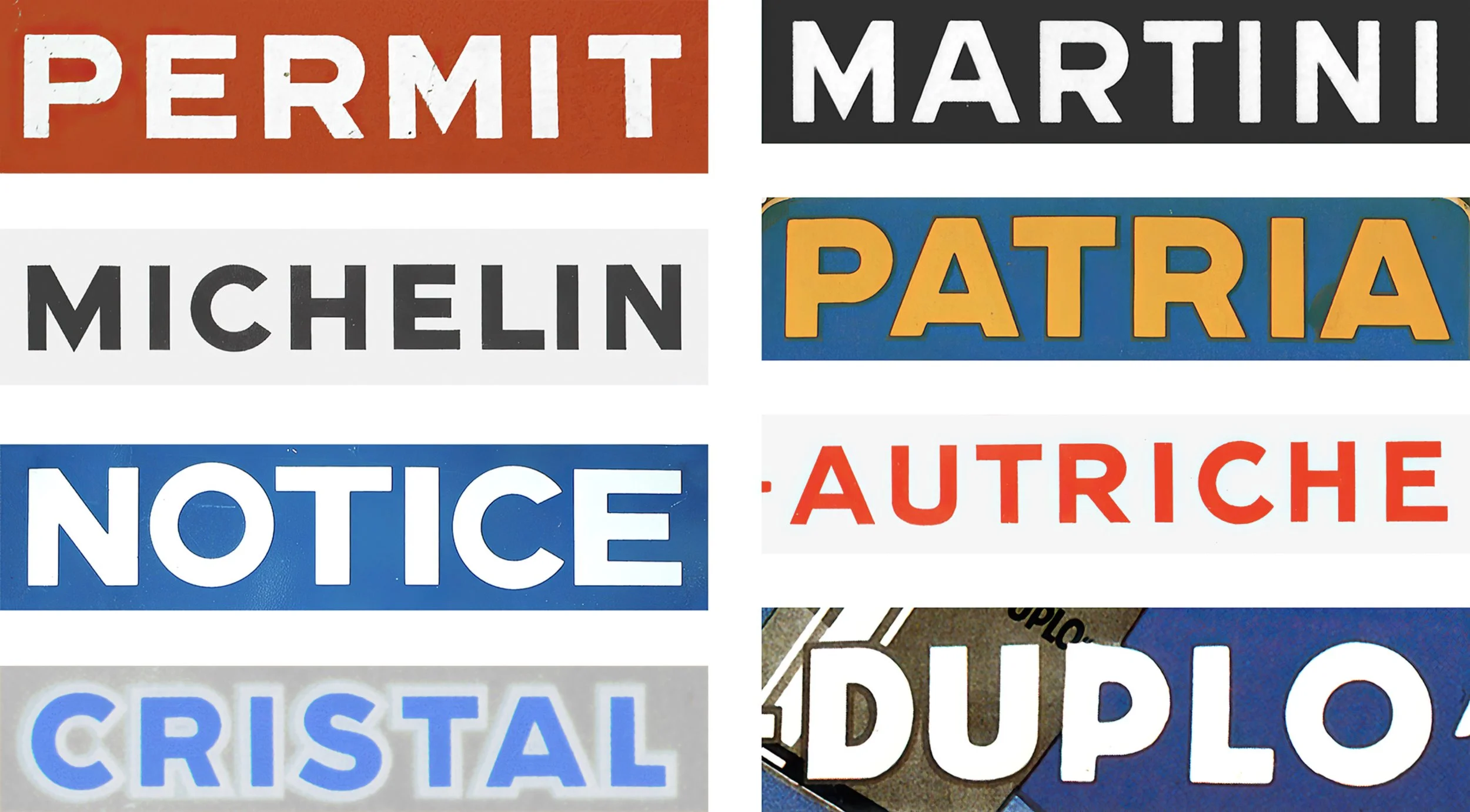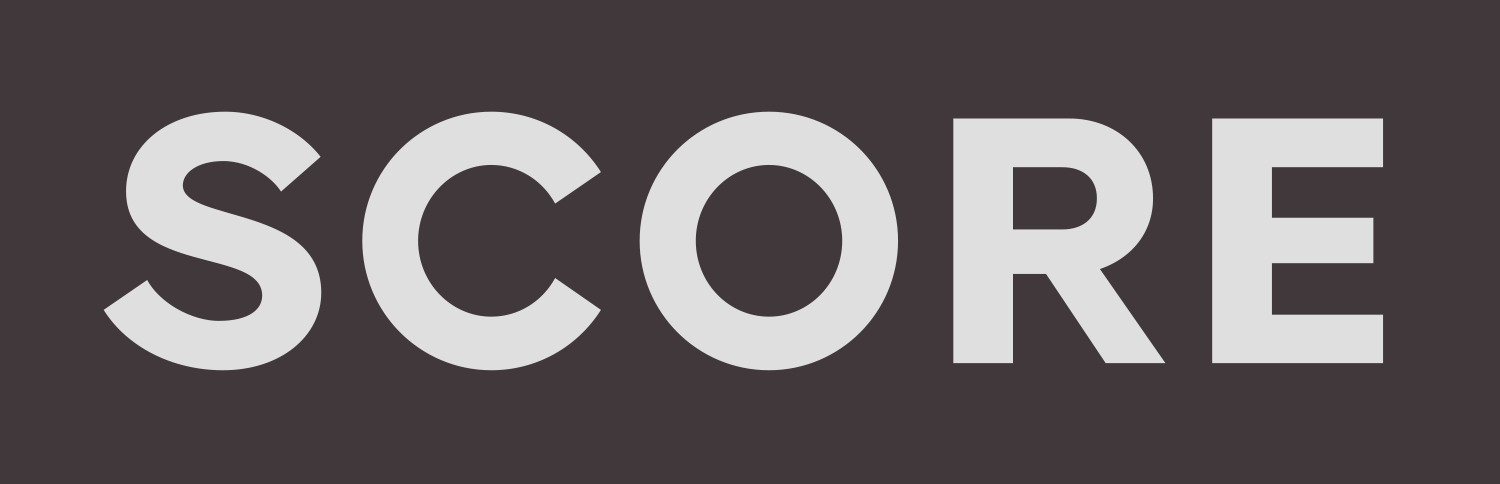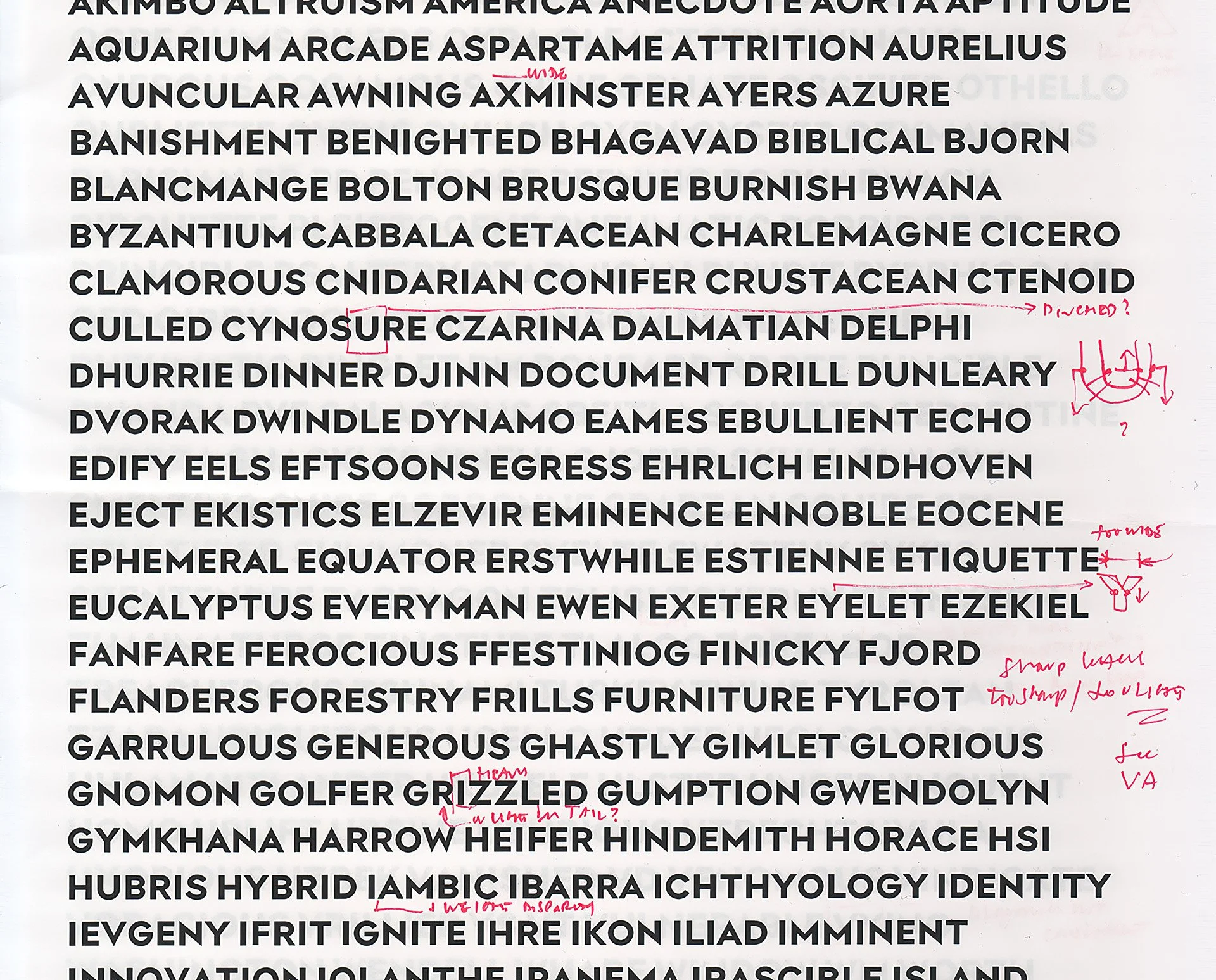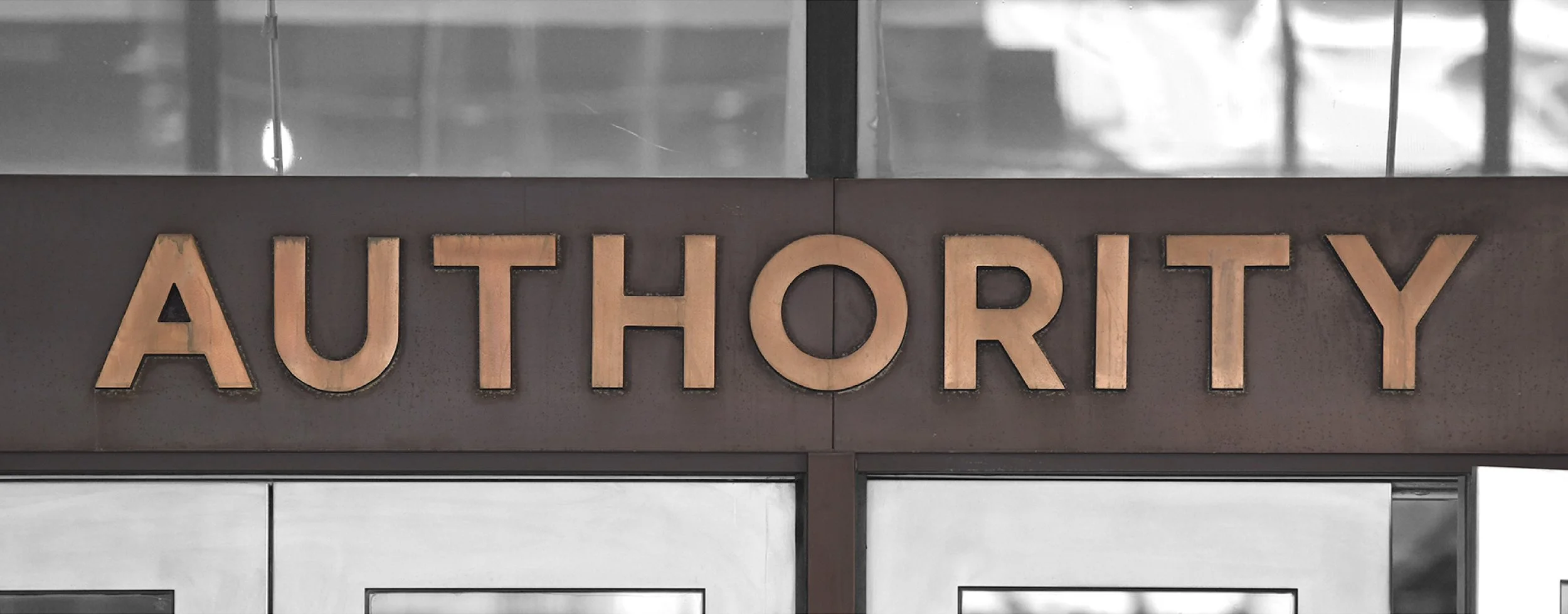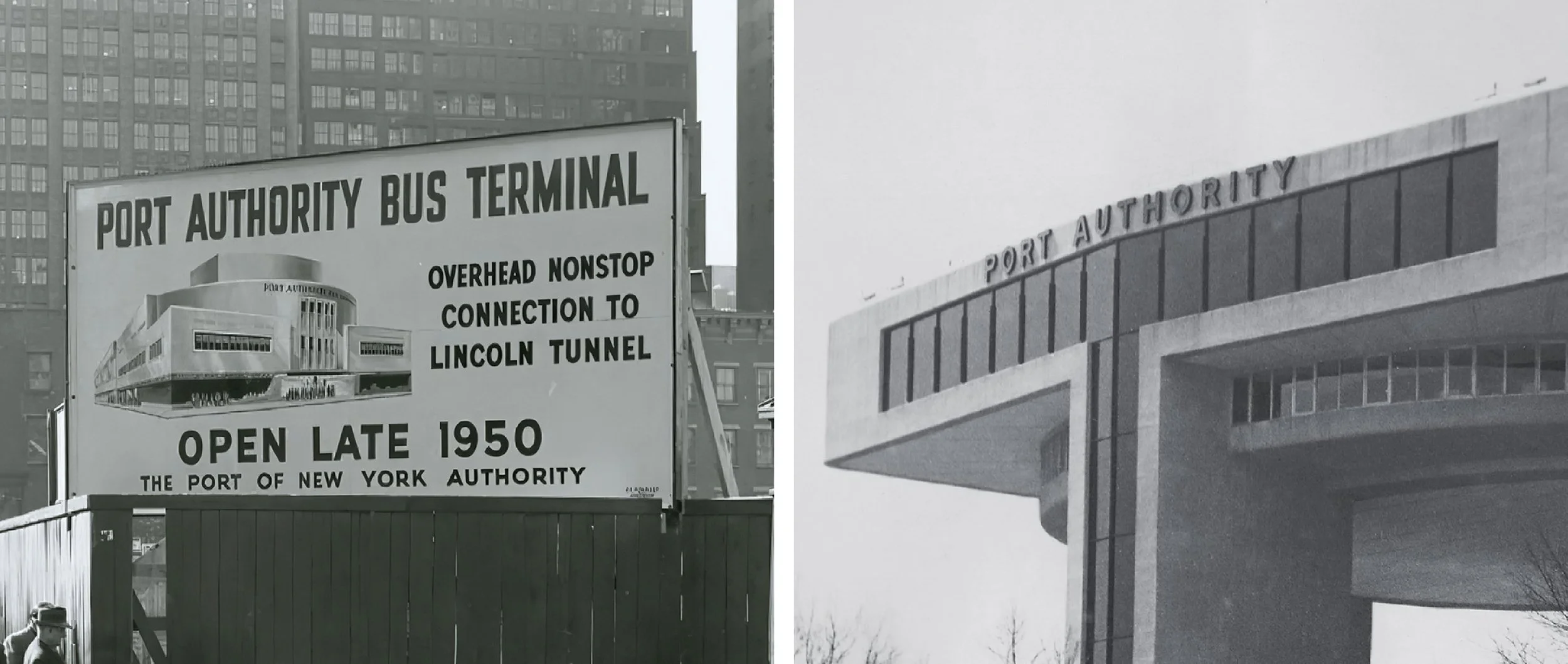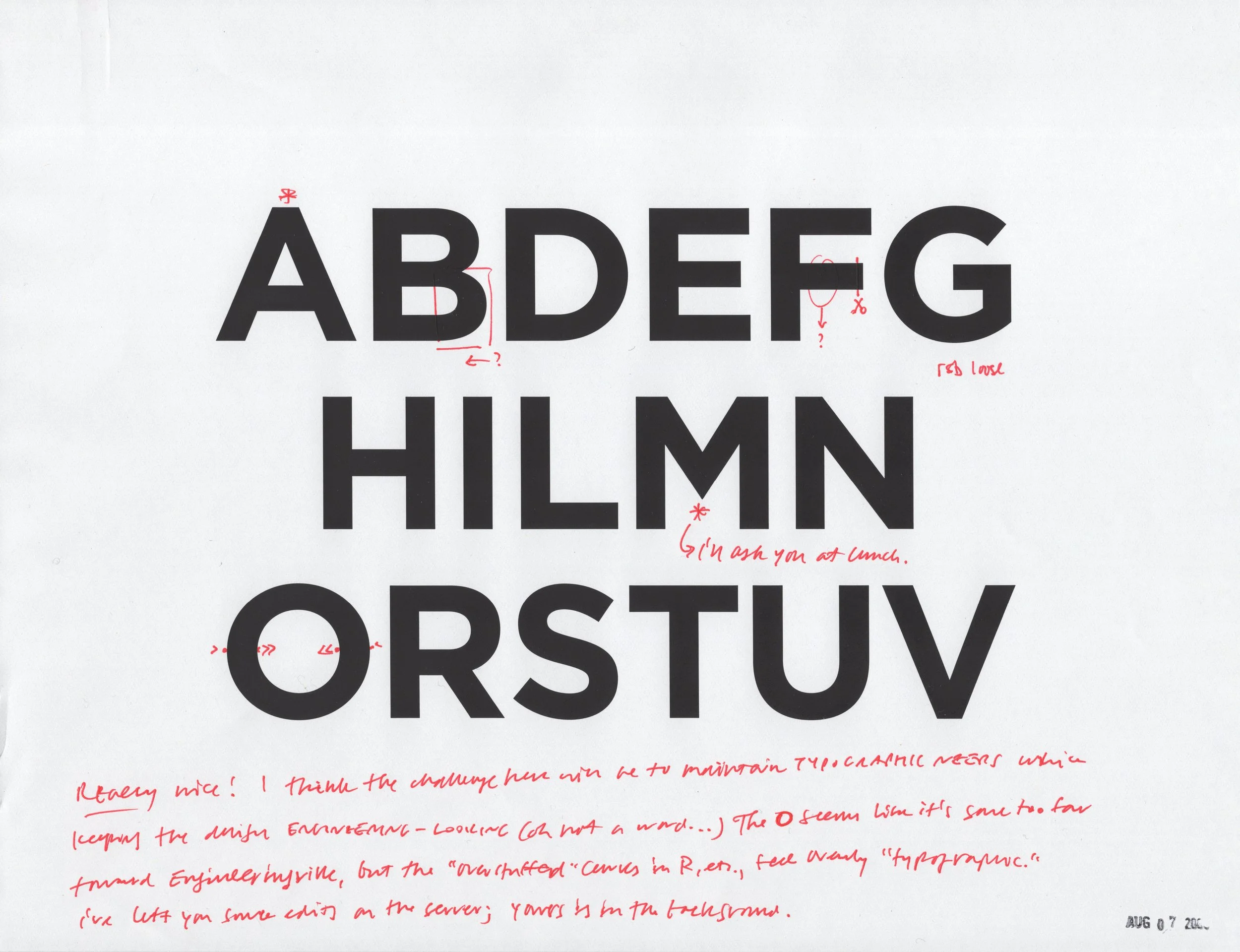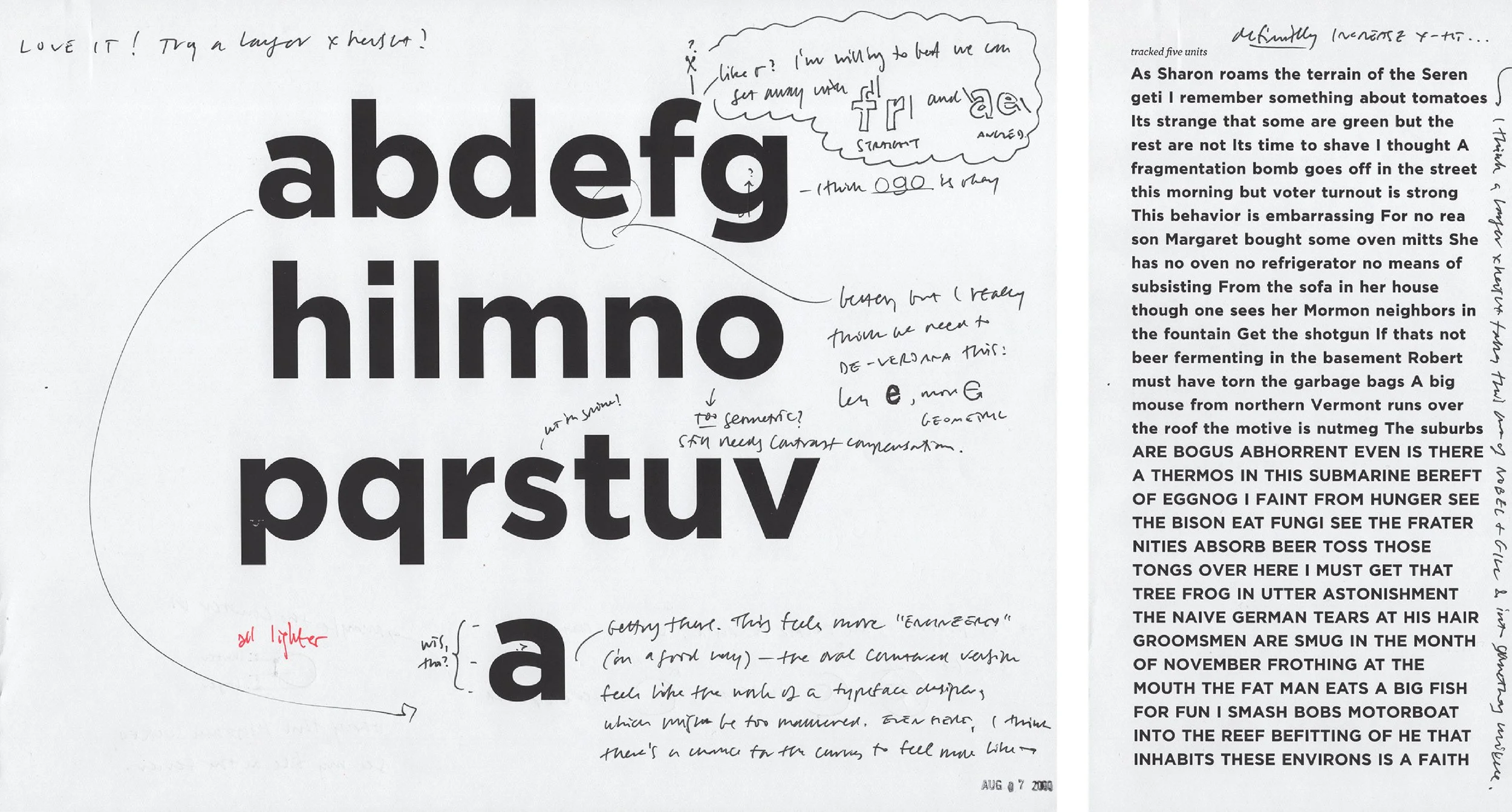
从纽约街头到总统竞选:一文读懂传奇字体 Gotham 的前世今生
如果要选出一款能代表现代城市精神的字体,Gotham 一定榜上有名。它曾出现在奥巴马 2008 年的竞选宣传中,也频繁活跃在海报、广告和品牌形象里,成为 21 世纪最具影响力的无衬线字体之一。
但它的故事,并不是从电脑屏幕开始,而是源自纽约街头那些无名却持久的字母。为什么这样「看似平凡」的字形,能够成长为全球舞台上的视觉语言?
本文改编自 Hoefler&Co. 创始人、Gotham 的设计者 Jonathan Hoefler 的自述文章,带你追溯这款字体的起源与崛起。
1 源于街头的字母灵感
这些街头字母虽然无名,但似乎一直存在,它们被画在玻璃上、铸在金属里、刻在石头上;既出现在战时通告中,也点缀过香水瓶和工业标志。但更多时候,它们出现在日常生活中:酒铺、理发店、花店的招牌,甚至电梯轿厢和商店橱窗。
设计文献几乎没有提及这些字母,这让人颇感意外。
设计潮流不断更替,但这些基本形态却始终显得现代、得体、不过时。
许多设计师的学习路径也是「倒着来」的:他们从身边现成的材料入手,再追溯字体的历史。最初,早期的 Mac 上的一百多种字体已经令人觉得丰富。但直到 1988 年,Jonathan Hoefler 进入 PushPin Group 下面的一家小型工作室,才真正接触到浩瀚的字体世界。
PushPin 的图书馆里摆满了字体样张书籍,宛如一部「化石记录」,展示着大量已随铅字与照排工艺消失的字体。夜晚,Hoefler 常在这些书里寻找理想的无衬线字体。最终他发现,这些形态并非源自传统字体,而是起于手工绘制的字母。
2 字体 VS 字母绘制
字体(Type)是预制、可重复组合的字形系统,而字母绘制(Lettering)则是一次性的、为特定场合量身定制的字形组合
。一个世纪前,字体排版只出现在书籍正文中,书籍封面、书脊或插图上的文字都是手绘字母,而非直接组合现成字体。
由于手写字母独立于字体存在,它发展出了自己独特的风格和传统:石印海报、雕刻钞票、镀金橱窗招牌、刻在墓碑上的字母,都是量身定制而非现成排版,每一种都展现了媒介特性和创作者习惯。
尽管字体与手写字母几个世纪以来互相影响(毕竟古腾堡的活字就是以手写字母为模型),但
似乎没有任何字体设计师尝试去捕捉 Hoefler 欣赏的这种手绘无衬线风格。
或许正是这个挑战,让他成为了一名字体设计师:这是一次不可抗拒的机会,可以探索未知领域,填补他感受到的空白。
3 从未竟之作到设计典范:Gotham 的诞生历程
3.1 新政雄鹰:Eagle Bold 的推出
从字体分类来看,Jonathan Hoefler 钟爱的字母,
融合了几何体的纯粹与怪诞体的温度,却避开了两者的缺陷
。它们像 Futura 一样清晰简洁,却没有几何体的刻板;它们兼具 Akzidenz-Grotesk 那种厚重亲切的特质,却比印刷字体更自然随性。
与 Helvetica 这类工业化的产物不同,这些街头字母看起来更真实可信:
不像是被「设计」出来的,而像是被「自然造就」的。
在字体与手写字母交汇的历史中,有一个值得注意的时刻,出现在罗斯福新政时期。为推动美国走出大萧条,美国国家复兴署(NRA)建立了统一的视觉体系:标志性的蓝色雄鹰、红白蓝黑的配色,以及直接、现代的无衬线字母。这些字母出现在商店橱窗、商品标签和胸针上,形成鲜明的视觉语言。
1933 年,美国铸字公司设计总监 Morris Fuller Benton 将这种手绘字母转化为字体,推出了 Eagle Bold。在他的手中,NRA 原有字母中的装饰性 Art Deco 特质被放大,原本为了易读性而采用钝角的 M 与 W,在新字体中被锐化,呼应了 NRA 首字母的尖锐笔画,使字体更具辨识度。
Eagle Bold 本身也带有矛盾:
一方面,它通过在字母结构中不断强化锐角,强调几何感
(如 G 的独特突起、Q 的三角尾部);
另一方面,它又放松了几何约束,让部分字母更温润亲切
(如 D 的非圆形曲线、S 的自然流动)。尽管 Jonathan Hoefler 并不完全喜欢这种风格,但他欣赏 Benton 的尝试,并认为这为自己在几何体和怪诞体之间开辟新可能留下了新的探索空间。
于是,1992 年夏天,Hoefler 开始着手设计一款通用、清晰、不可动摇的无衬线字体,
灵感正是来自他在街头海报与招牌中见到的那些「无名字母」。
3.2 初步尝试:更平稳坚定的 Typeface X
1992 年,Jonathan Hoefler 绘制了一组大写字母,命名为 Typeface X,呈现了他记忆中的手绘无衬线风格。
和 Benton 一样,他希望从几何体与怪诞体中汲取养分,但目标并非追求华丽,而是打造一种坚定、清晰的字体。
不同于 Eagle Bold 宽窄交错的节奏,Typeface X 更接近工业字体,字宽趋于统一,排版更平稳。
它延续了怪诞体中椭圆形的 S,又保留了几何体近乎圆形的 O,看似简单直接,却暗中融入更细腻的调整,让字体多了几分温度。
Hoefler 希望这种设计能超越时间,像街头橱窗和海报上的无衬线字母那样,经得起数十年的潮流更替。
虽然 1992 年的原型仍显青涩
(例如 R 的腿略显单薄,C 的内部尚需打磨),
却已传达出他追寻的核心风格。
然而在 1993 年,Typeface X 的最终打样让问题彻底暴露。
此前他忽视了一个关键细节:Benton设计的 Eagle Bold 从未用于 18pt 以下的小字号,这其实是在回避几何体在小尺寸下的先天缺陷。而 Hoefler 原以为 Typeface X 的厚重笔画能跨越字号的限制,直到高分辨率打印机揭穿了这个幻想。
在小字号下,Typeface X 的尖锐笔画几乎消失,M、N 的外角显得过小,字形仿佛缩短了高度;A、V 的尖角又制造出大片无法调和的空白。
他清楚,钝化这些尖角也许能解决问题,正如 Paul Renner 在 Futura 上做过的妥协,但那将牺牲大字号下的锐利与闪光。于是,Typeface X 被搁置。
随后,《体育画报》邀请他为 Champion Gothic 设计更细的版本,《纽约时报杂志》则委托他开发一款小字号用的无衬线字体。这两项庞大项目孕育了 Knockout 家族,并占据了他整个 1994 年。
而就在这一年,他在时报大楼附近的偶然一瞥,遇见了彻底改变 Typeface X 命运的字母,也即 Gotham 焕发新生的转折点。
3.3 机会来临:新合作,新起点
纽约剧院区时代广场西侧的港务局巴士总站,是城市最繁忙的交通枢纽之一,也是一处市政工程巧思之作,但灰暗且不适合久留。
大门上方,一组写着“PORT AUTHORITY BUS TERMINAL”的字母,风格完美体现了 Hoefler 多年来追寻的手写无衬线字母精髓。这块牌匾可能属于 1950 年的原建筑,并在 1979 年扩建时得以保留。后来他才发现,这种字母风格在港务局其他宣传材料中也有体现,包括 1949 年的施工现场标牌,以及 1964 年世博会的建筑字体。
这些字母看似朴素,却工艺精湛,连 S 和 B 等复杂字母都展现出高超设计感。对于 Hoefler 来说,这块牌匾明确了大写 A 的顶端应平而非尖。他将港务局的字母视为新字体的最终范本,为 Gotham 的诞生奠定了基础。
在小工作室忙碌的几年里,Typeface X 这个项目一直搁置。Knockout 系列之后,Hoefler 又陆续接下 Hoefler Titling、Verlag 和 Mercury 等复杂字体项目,同时拓展零售字体业务和扩充团队。即便如此,他仍留意机会,希望有朝一日能重启那个未完成的项目。
机会终于在 2000 年出现,当时他迎来了新的合作伙伴 Tobias Frere-Jones。
两人都热爱无名的工业风格字母形态:Tobias 早年设计了 Interstate 字体,改编自 1948 年 Theodore Forbes 为公路标志创作的标准字母;Hoefler 则先后设计了 Champion Gothic 和 Knockout,延续了美国 19 世纪末哥特木活字的灵魂。
两人的首次合作是受 Pentagram 的 Michael Bierut 委托,为戈登·邦夏在纽约公园大道设计的摩天大楼 Lever House 定制字体。
随后,GQ 杂志委托他们为杂志设计「现代简洁」的字体
,这次,他们的灵感终于来自 Port Authority 巴士总站的标牌,
Hoefler 多年追寻的经典字母终于有机会转化为新字体。
3.4 正式开工:Gotham 的首次成型
2000 年夏天,Hoefler 与 Frere-Jones 受 GQ 委托,借助更多参考材料,决定从零开始设计新字体。他们以 Port Authority 招牌为原型绘制字母,并补齐 D、F、G、V 等字母,形成字体设计常用的“hamburgevonstifd”测试集。Hoefler 在校样上做了笔记和微调,继续思考 Benton 字体的几何感与排版感平衡,也总结了此前 Typeface X 的经验教训。(M 字母尖角旁的一条注释写着:“午餐时问你。”)
Gotham 最独特之处,是它的小写字母。
在研究的海报、招牌、霓虹和钢铁字母中,小写几乎不存在。缺乏范本,设计团队必须完全原创,让小写也承载大写字母的核心精神。
初稿中,小写偏小、升部偏高,带有浓厚怀旧感。
通过增大字母、缩短升部、收紧字距,并调整关键字母如 e、f、g,
字体的整体气质立刻改变,从而确立了新的设计原则。
随着小写完善、数字与符号加入,Gotham 家族逐渐扩展到不同字重。Tobias 的 Gotham Light 保留粗体特色,又赋予字体新语气:简洁坚定,又可优雅、轻快或俏皮。
虽然 GQ 最初只委托了一个小型字体家族,但 Jonathan Hoefler 一开始就觉得
Gotham 可以在更广的风格范围内展现个性
。最初的设计仅包括 Light 与 Bold(以及通过插值生成的 Book 和 Medium),随后快速增加了匹配的斜体和一套窄体。
Tobias 曾建议给 Gotham Condensed 设计「体育场形」的 O 字,用平直的侧边呼应「工业风字母」的理念。但 Hoefler 更倾向于基于椭圆的字形:一方面,他在 Champion Gothic 与 Knockout 中已经尝试过笔画平直的无衬线;另一方面,体育场形字母太容易让人联想到九十年代回潮的德国 DIN 字体。
最终,两人选择了椭圆模型,并在 2001 年新加入的设计师 Jesse Ragan 帮助下,将字族扩展为更细和更粗的字重,Gotham Condensed 从四款增至九款。至此,Gotham 的字宽和字重范围都有了明确界限,团队开始填充中间的过渡字重。
3.5 设计空间的延展:Gotham 家族完善
2000 年代初,Gotham 已为多家杂志和报纸客户定制了中间宽度版本,以适应窄栏目的需求。随着定制需求增多,团队将设计空间分为两条路径:紧凑的 Gotham Narrow 和更纤细的 Gotham Extra Narrow。
大选结束后,Gotham 成为白宫官方沟通的主力字体。2012 年,Gotham 再次服务于奥巴马的连任,这次还加入了加衬线的「Obama–Biden」标志。字体在第二任期继续扮演官方声音,并延伸至 2014 年成立的奥巴马基金会。自此,Gotham 成为政界的首选字体,无论党派、地域还是国家。到 2018 年中期选举,近五十位候选人使用它来塑造竞选形象,美联社甚至称其为「十年之字」。
2011 年,纽约现代艺术博物馆将 Gotham 收入永久馆藏,与赖特的流水别墅模型和苹果早期 Macintosh 电脑并列。
策展人 Paola Antonelli 指出:“优秀的字体应当被纳入 MoMA 的收藏。”
对设计师而言,Gotham 的成功远超预期。它不仅成为日常视觉的一部分,也不断启发新的字体创作。正如《新闻周刊》所说,Gotham 已是一部「现代经典」。
5 结语
从纽约街头的无名字母,到白宫与世界舞台的视觉语言,Gotham 的旅程是一段独特的设计传奇。它的完成并非一蹴而就,而是经历了多番峰回路转。
凝结着字体设计师心血与巧思的 Gotham,
不仅回应了一个时代对清晰、坚定与亲和的诉求,也证明了字体能深刻影响文化与历史,成为设计力量的长久注解。